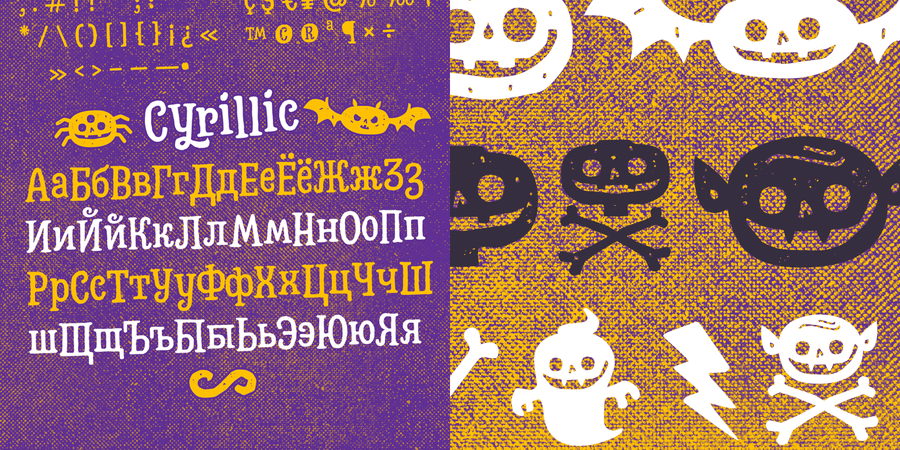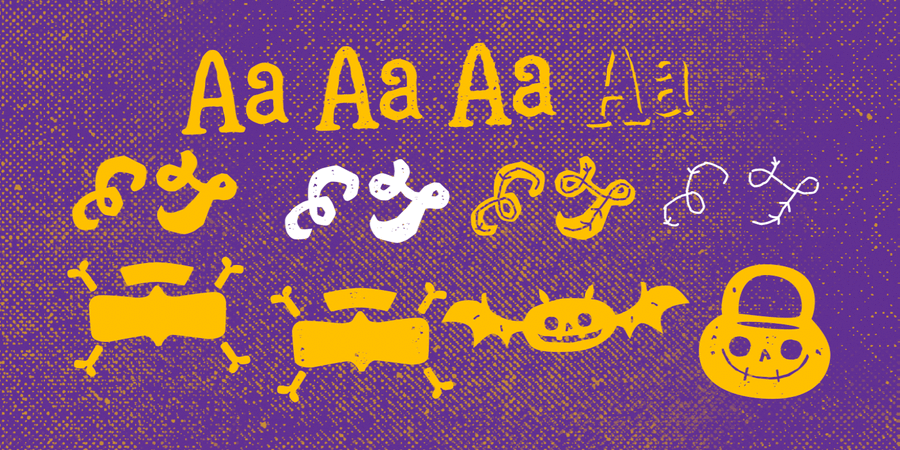
Опис гарнітури Hatter Display ProЦе вдосконалена версія шрифту Божевільного Капелюшника. Він містить 12 накреслень, які підтримують кирилицю, розчерки, альтернативні гліфи, символи та орнаменти – усе для створення розважальної графіки.
Цей божевільний шрифт створив Родріго Арая Салас у 2017 році.
Асоціації з сімейством шрифтів Hatter Display ProОсобистість і характер гарнітури:
колючий, ролевий, кущистий, рослинний, лісовий, складний, химерний, готичний, закручений, кріповий, старомодний, тісний, оригінальний, характерний, грайливий, самобутній, кучерявий, артистичний, танцюючий, цікавий, декоративний, динамічний, колоритний, живий, крафтовий, чарівний, неформальний, непосидючий, неслухняний, пустотливий, рухливий, задерикуватий, рукотворний, натуральний, вигадливий, домашній, органічний, казковий, старовинний, ламповий, ремісничий, фермерський, творчий, чаклунський, магічний, святковий, веселий, смішний, жартівливий, стрибучий, хуліганський, наївний, епатажний, мультяшний, дотепний, осінній, зловісний, злий, цвинтарний, страшний, мертвий, фрік, пекельний, дивний, божевільний, окультний, таємничий, загадковий, експериментальний, моторошний, гарбузовий, повзучий, гнучкий, гарячий, вогняний, фантастичний, артізанальний, екзотичний, вернакулярний, макабричний, нервовий, зимовий, теплий, грубий, недбалий, сніжний, новорічний, пухнастий, вуличний, побутовий, дитячий, емоційний, яскравий, радісний, кольоровий, природний, активний, прикольний, виразний, неохайний, затишний, доброзичливий, дикий, потішний, гулящий, смачний, помітний, сільський, зелений, кустарний, саморобний, нерівний, сухий, тонкий, крихкий, гострий, вампірський, звіриний